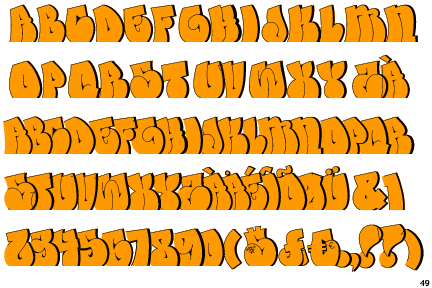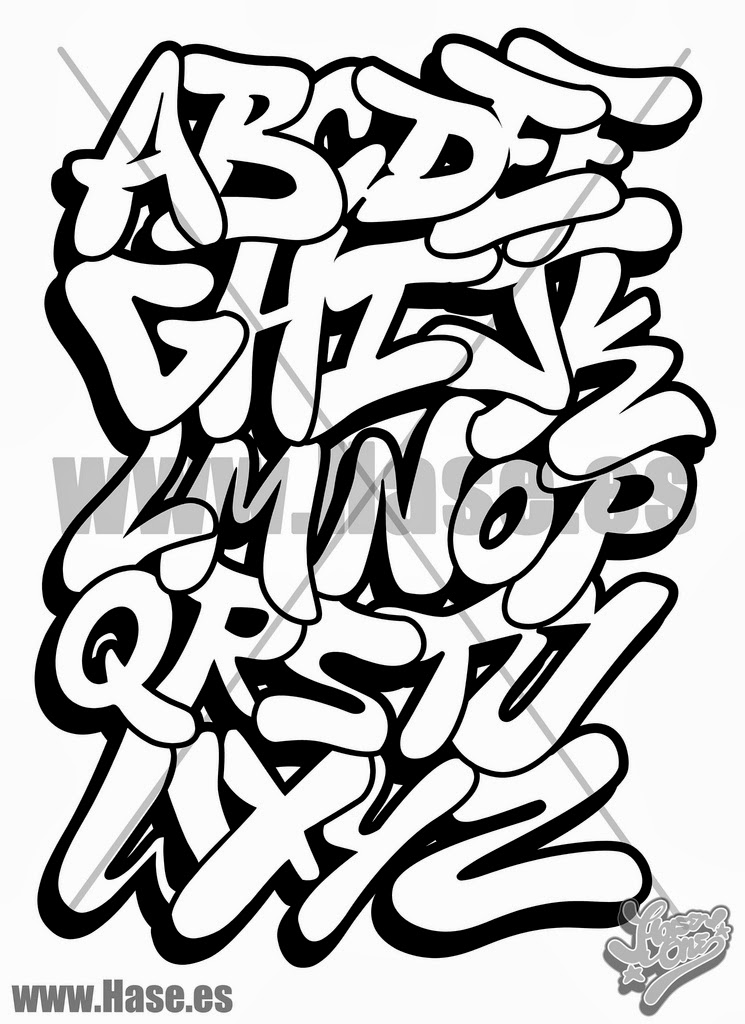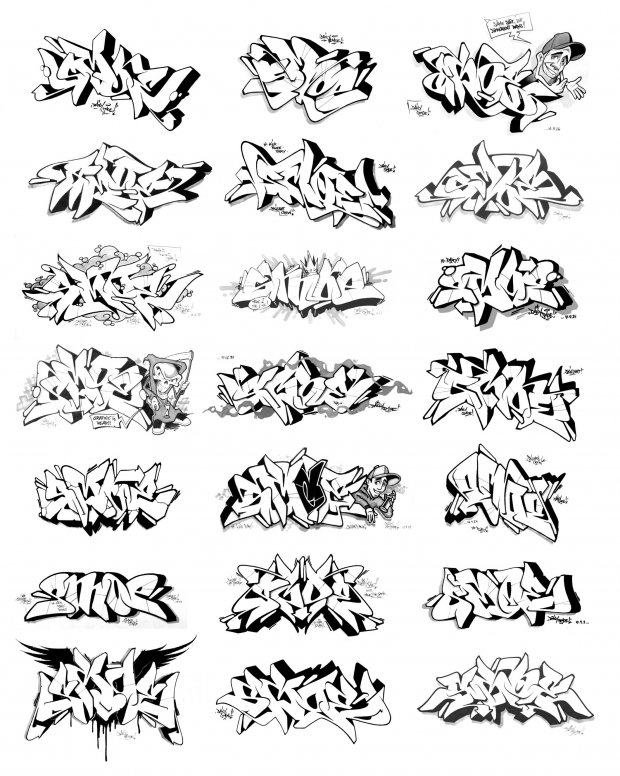
15 лучших бесплатных шрифтов для граффити
Вы ищете уникальный шрифт для дизайна плаката к фильму или обложки журнала? Тогда подумайте о шрифте для граффити.
Эти шрифты часто имеют уникальный дизайн и смелый вид, привлекающий внимание.
В этом посте мы собрали лучшие бесплатные шрифты для граффити со всего Интернета. Большинство из них можно бесплатно использовать в личных проектах, но некоторые можно использовать и в коммерческих проектах.
Шрифт Hosp был разработан для творческих людей.Это отличный выбор для любого современного проекта, который требует смелого внешнего вида. Шрифт включает прописные буквы, цифры и знаки препинания. Это бесплатно для личного пользования.
Шрифт Sprite поставляется в 3 разных стилях, и вы можете использовать его, когда вам нужен вид граффити, но при этом вы хотите сохранить читаемость. Шрифт бесплатный для личного и коммерческого использования и поставляется с лицензиями для настольных компьютеров и веб-шрифтов.
Шрифт Multicolored graffiti
Graffiti Punk Kid Font
Fresh Air Handwritten Graffiti Font
Graffiti Italiano Brush Font
Набор шрифтов Graffiti
Шрифт Reis Graffiti
Шрифт Graffiti Night Flight Marker
Рисованный шрифт Graffiti
Шрифт Graffiti Design
А вот интересная подборка шрифтов для Photoshop в стиле Граффити. Я думаю, она пригодится многим.